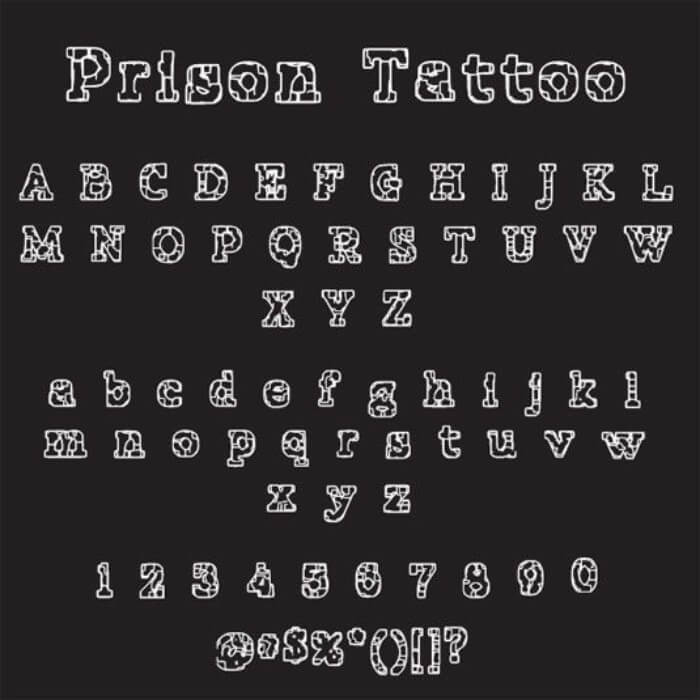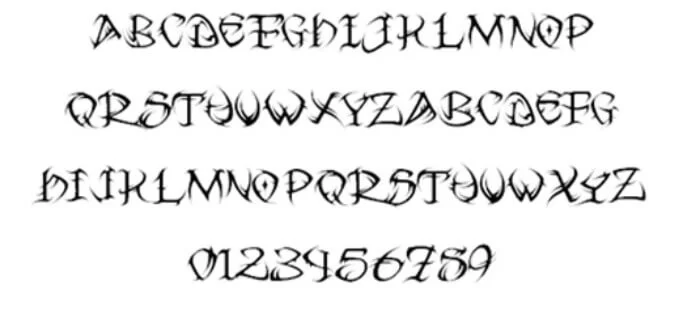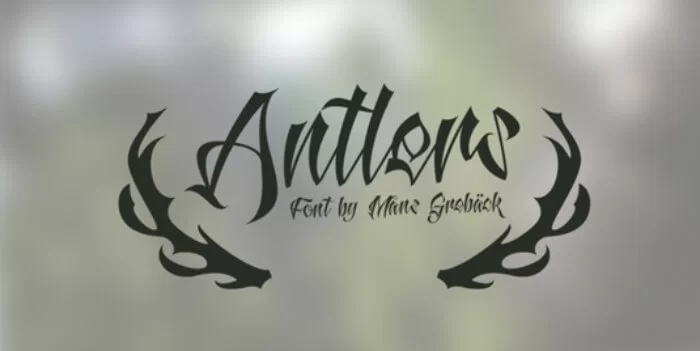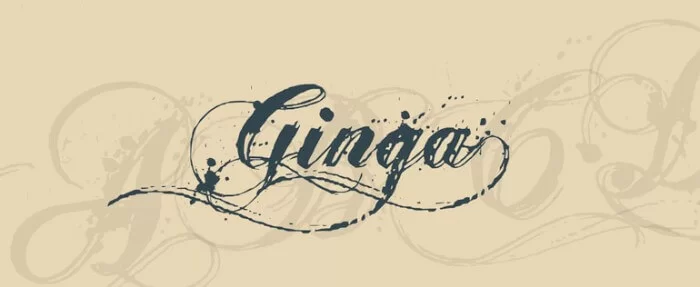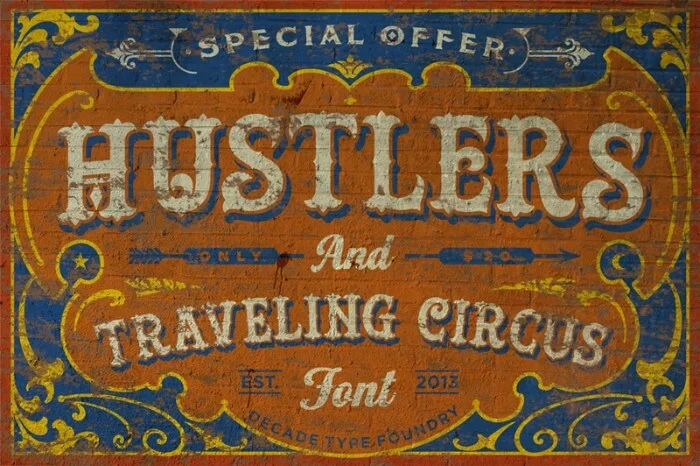
Die 50 besten kostenlosen Tattoo-Schriftarten für Körperkunst
Veröffentlicht: 2023-01-11Tattoo-Schriftarten haben es geschafft, unter Tattoo-Liebhabern ziemlich viel Aufhebens zu machen. Wir Menschen haben eine Affinität zu Schriften mit handgezeichnetem Styling.
Tattoo-Schriftarten tragen dieses Element perfekt, während sie einige dicke und kräftige Striche hinzufügen. Dies macht jede Aussage, die mit Tattoo-Schriften gemacht wird, sehr auffällig und ansprechend.
Wenn Sie sich für diese Art von Typografie interessieren, sind Sie hier genau richtig. Hier haben wir eine Liste mit einigen der beeindruckendsten Tattoo-Schriftarten zusammengestellt.
Es wurde viel Wert darauf gelegt, dass bei den verschiedenen Zeichensätzen und Glyphen ein gewisses Maß an Vielfalt erhalten bleibt, sodass Sie viele Gestaltungsmöglichkeiten haben.
Top-Schriftarten für Tattoo-Liebhaber
Immer bei dir
Beginnend mit unserer Liste haben wir die Schriftart „Always Beside You“. Die Schrift weist viele Schwünge und Kurven auf, um ein Design im alten englischen Stil zu schaffen. Und dann fügt die leicht kratzige Schreibschrift mehr Tiefe hinzu.
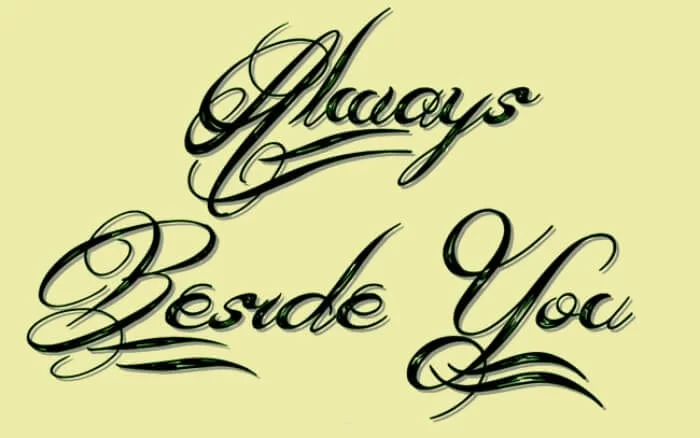
Mama
Mom ist eine äußerst beliebte Tattoo-Schriftart , auf die Sie gestoßen sein sollten. Die Schriftarten verwenden eine fette Struktur, um einen Buchstaben zu erstellen, und verwenden dann dünne Linien, um den Aufbau des Buchstabens zu vervollständigen.
Engel Tränen
Mit „Angel Tears“ haben Sie Buchstabenformen mit abwechselnd dicken und dünnen Strichen. Es gibt auch ein Element in diesen Schriftarten, das es so aussehen lässt, als wäre es skizziert worden. Insgesamt eine edle und robuste Schriftart.
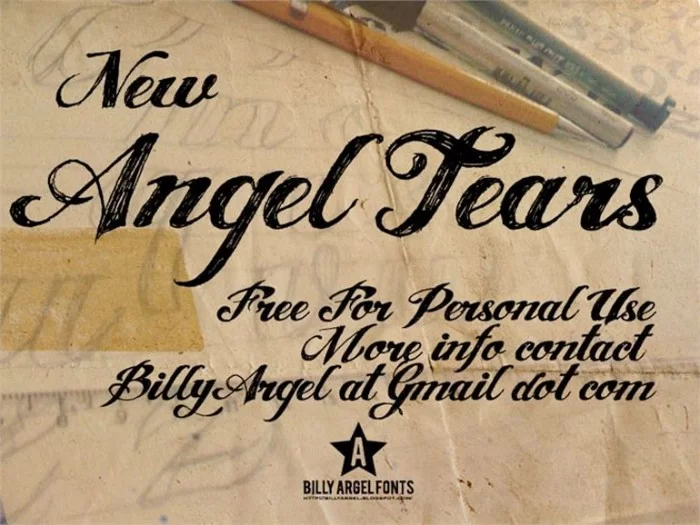
Reditum
Reditum ist eine kalligrafische Schrift. Es ist sicher, den Stilfaktor Ihres Projekts zu verbessern, wenn es verwendet wird. Mit geschwungenen Buchstaben, die abwechselnd dicke und dünne Linien verwenden, haben die Schriften auch etwas Menschliches.
Stammesdrache
Tribal Dragon hat einen spielerischen Ansatz, um seine verschiedenen Schriftarten zu erstellen. Alle Buchstaben sind im Wesentlichen dünn und scheinen scheinbar von Drachen gemacht zu sein, die in einer bestimmten Position liegen.
Lina-Skript
Lina Script hat ein elegantes Designelement, gepaart mit einem frechen Graffiti-Touch. Sie können sehen, dass es in Projekten im Zusammenhang mit Musikbands verwendet wird, insbesondere Bands, die zum Groll- oder Metal-Genre gehören.
Rustikales Liebestattoo
Pentagon
Die Pentagon-Schriftart hat einen Designstil, der aussieht, als stamme er direkt aus einem US-Wahlkampf aus den 70er oder 80er Jahren. Die Schriftarten sind fett, einzigartig und mit Sternen übersät.
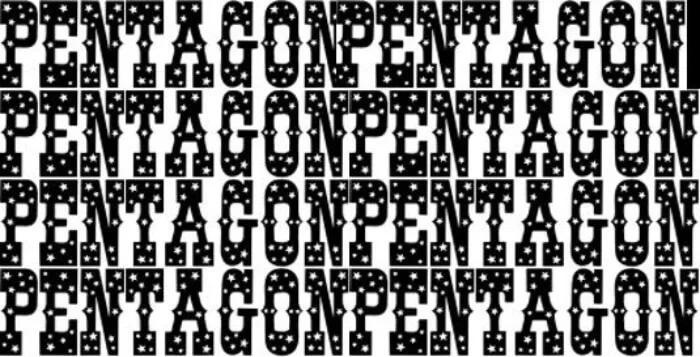
Zitronengelee
Lemon Jelly bietet große und freundlich wirkende Schriften. Nichts ist zu übertrieben oder stark ausgearbeitet, was die Schriften für alle möglichen Anwendungsfälle lesbar macht.
Angilla Tattoo Schriftart
Angilla Tattoo kommt mit einer dicken Schrift, begleitet von schönen Schwüngen, die dem Schriftzug ein Flair verleihen können. Der beste Aspekt ist, dass es Stil liefert, ohne die Lesbarkeit zu beeinträchtigen.
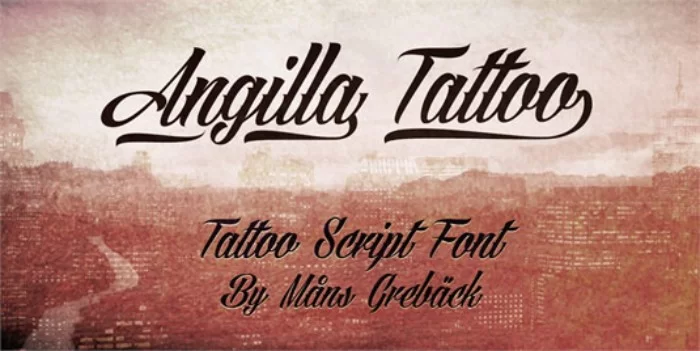
Kleiner Herr
Die Schriftart Little Lord hat einen schönen Fluss zwischen Groß- und Kleinbuchstaben, obwohl erstere schwülstige Effekte haben und letztere sauber und minimal sind.
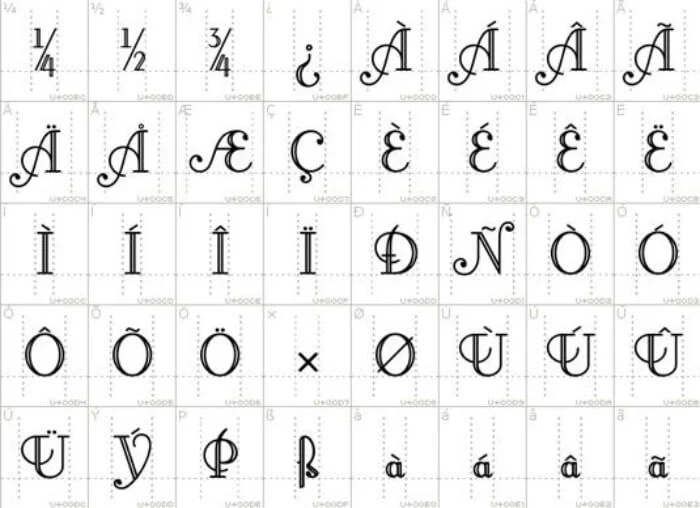
Matrosengekritzel
Sailor Scrawl bietet eine Sammlung einzigartiger robuster Schriftarten. Jede der Schriftarten wird von einer kleinen Raute begleitet, die sich in der Mitte der Buchstaben befindet.
Captain Cook Tattoo Schriftart
Diese Tattoo-Schriftart ist nach Captain James Cook benannt. Dies ist eine interessante Tattoo-Schriftart, die in einer Umriss- und einer halbgefüllten Version erhältlich ist.
VTKS-Tätowierung
Die Schriften mit VTKS sind gut gestaltet und sehen sehr schick aus. Es vermittelt ein Gefühl von Old-School-Design. Die Buchstaben fühlen sich an wie angezündet.
Feder
Spring bietet eine Sammlung von Schriften, an denen intensiv gearbeitet wurde, um einige aufwendige und aufwändige Designs zu bieten. Mit dem Design ist ein Gefühl von Unfug und Mysterium verbunden.
Champignon
Die mit Champignon gelieferten Schriften bieten mit ihrem kursiven Stil ein elegantes Design. Diese Schriftart wird auch in der Lage sein, einen Sinn für menschliche Handschrift zu emulieren.
Unzialish bietet eine Schriftart im alten Stil, die einigen Elementen ähnelt, die wir bei ägyptischen Hieroglyphen beobachten. Mit abwechselnd dicken und dünnen Strichen, breiten Positionen, langen Linien und schweren Serifen hat es einen keltischen Stil in seinem Design.
Tuamotu
Als nächstes haben wir Tuamotu. Es ist ein lustiger Schriftstil mit großen Blockbuchstaben, die einige Tribal-Style-Designs mit all seinen Schriftarten enthalten. Der Schriftstil hat auch eine gewisse kindliche Anziehungskraft, was ihn perfekt macht, um einige lebhafte Ereignisse hervorzuheben.